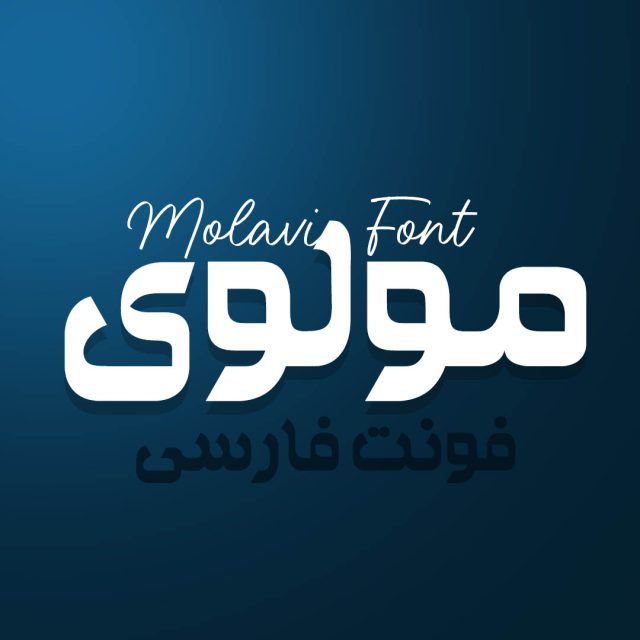
دانلود فونت فارسی مولوی Molavi Font
دانلود فونت تایپوگرافی فارسی مولوی: مولوی،فونت دیگری است که در این محصول از دیاکوگرافیک می خواهیم به شما معرفی کنیم! فونتی که با طراحی ویژه خود مناسب تایپوگرافی های حرفه ای می باشد.این فونت به صورت فرمت های وب فونت نیز آماده شده است که قابل استفاده در طراحی وب می باشد.فونت مولوی رو میتونید از سایت دیاکوگرافیک دریافت کنید و در طراحی های مختلف استفاده کنید.
فونت تایپوگرافی مولوی
برخی ویژگی های فونت مولوی
- مناسب برای طراحی لوگو تایپ های حرفه ای
- مناسب طراحی تامبنیل و کاور یوتیوب
- مناسب طراحی های اینستاگرامی و استوری
- مناسب طراحی لوگو تایپ های حرفه ای
- مناسب طراحی پوستر های حرفه ای
پیشنمایش و نمونه تایپ های فونت مولوی